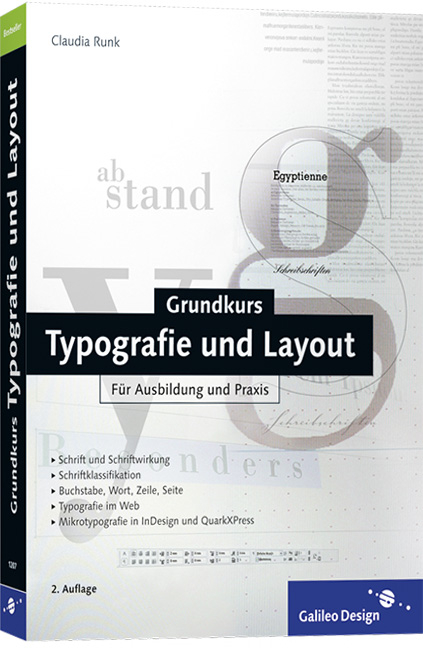
Grundkurs Typografie und Layout
Aus dem Inhalt:
- Schrift
- Schriftgeschichte, Schriftkünstler
- Schriftwahl und Schriftwirkung
- Schriftklassifikation
- Buchstabe, Zahl, Zeichen
- Abstand, Laufweite, Ausrichtung
- Serifen, Ligaturen
- Einzug und Initial
- Typo in InDesign & QuarkXPress
- Seite und Raumaufteilung
- Zeilen und Spalten
- Papierformate, Satzspiegel
- Gestaltungsraster, Bildplatzierung
- Registerhaltigkeit, Beschnitt
- Layoutfehler vermeiden
- Anforderung und Wirkung
- Typografie im Web
- Schrifttechnologie
- Schreibregeln
1 Schriftentwicklung 15
1.1 Entwicklung 16
... 3500 v. Chr. und die Sumerer 16
... 3000 v. Chr. und die Hieroglyphen 17
... 1200 v. Chr. und die Phönizier 18
... 500 v. Chr. und die Griechen 19
... 100 n. Chr. und die Römische Kapitalis 20
... 800 und die Karolingische Minuskel 22
... 1000 und die Romanik 23
... 1200 und die hochgestreckte Gotik 24
... 1400 und der Beginn der Renaissance 25
... 1450 und Gutenberg 26
... 1500, die Gebrochenen Schriften und die
... Französische Renaissance-Antiqua 27
... 500 und die Kursive 28
... 1700 und Barock und Rokoko 29
... 1800 und der Klassizismus 30
... 1880 und der Jugendstil 32
... 1900, die Times und die serifenlosen Schriften 33
... 1920 und das Bauhaus 34
... 1950 und die Schweizer Typografie 36
... 70er, 80er, 90er und die Einführung des DTP 36
... 1990 bis heute 39
... Pixel- und Screenfonts 39
1.2 Schriftschnitt und Schriftfamilien 40
... Ist Italic eine Kursive? 40
... Frutiger und seine Zahlen 41
... MultipleMaster 42
... Schrift als Gebrauchsinstrument 43
... Schriftenwelle in der Industrialisierung 43
... Experten 44
... Kapitälchen 44
... Falsche Kapitälchen – ein Kapitalverbrechen? 45
1.3 Schriftklassifikation 46
... Warum überhaupt Klassen? 46
... Schriftklassifikation nach DIN 46
... 1. Klasse: Venezianische Renaissance-Antiqua 47
... 2. Klasse: Französische Renaissance-Antiqua (Mediäval) 48
... 3. Klasse: Barock-Antiqua 49
... 4. Klasse: Klassizistische Antiqua 50
... 5. Klasse: Serifenbetonte Linear-Antiqua 51
... 6. Klasse: Serifenlose Linear-Antiqua 52
... 7. Klasse: Antiqua-Varianten 53
... 8. Klasse: Schreibschriften 54
... 9. Klasse: Handschriftliche Antiqua 54
... 10. Klasse: Gebrochene Schriften 56
... 11. Klasse: Fremdsprachliche Schriften 58
1.4 DIN 16518 von 1998 58
1.5 Beinert-Matrix 59
1.6 Schriftkünstler 60
... Otl Aicher 60
... Neville Brody 61
... Tobias Frere-Jones 62
... Adrian Frutiger 63
... Claude Garamond 64
... Luc(as) de Groot 65
... Rudolf Koch 66
... Günter Gerhard Lange 67
... Hans Eduard Meier 68
... Stanley Morison 69
... Jim Parkinson 70
... Jean-François Porchez 71
... Paul Renner 72
... Werner Schneider 73
... Erik Spiekermann 74
... Ludwig Sütterlin 75
... Jan Tschichold 76
... Kurt Weidemann 77
... Hermann Zapf 78
1.7 Typografisches Maßsystem 79
... Didot-Punkt 79
... DTP-Punkt 79
... Pica-Point 79
... Typometer 80
2 Das Zeichen 83
2.1 Der Buchstabe 84
... Form 84
... Schriftgröße 85
... Der Bleisatz in wenigen Worten 86
... Kegelgröße und Schriftgröße 86
... Bleisatz und Digitalsatz? 87
... Weitere Faktoren für die Schriftgrößenmessung 88
... Schriftgröße per Versalhöhe 88
... Versalhöhenbeispiele 88
... Versalhöhen 89
... Begriffsdefinition 90
2.2 Serifen 92
... Ursprung der Serifen 92
... Serif oder SansSerif 93
... Humanistische serifenlose Schrift 94
... Der persönliche Stil 95
2.3 Ligaturen 96
... Buchstabenform 96
... Voraussetzung 97
... OpenType 97
2.4 Zahlen 98
... Arabische Zahlen 98
... Römische Zahlen 98
... Aufbau des arabischen Zahlensystems 99
... Mediäval- und Versalziffern 99
2.5 Auszeichnungen 100
... Ästhetische und optische Auszeichnungen 100
... Sparsame Verwendung optischer Auszeichnungen 101
2.6 Lesegewohnheiten 102
... Art und Weise des Lesens: die Sakkaden 102
... Ruhe zwischen den Sakkaden 103
... Erschwerte Lesbarkeit durch breite Schrift 103
... Reihenfolge der Buchstaben 103
... Die obere Hälfte des Textes 104
... Grauwert 104
2.7 Leere Räume 106
... Geviert – die feste Größe 106
... Geviert statt flexible Räume 106
2.8 Wortabstand 107
... Die optimale Größe 107
... Große Größen bei dünnen Schriften 108
... Unfreiwillige Größenänderung 108
... Manuelle Bearbeitung 109
... Optische Löcher 109
2.9 Der Zeichenabstand 110
... Automatisch optimale Laufweiten 110
... Laufweiten und Schriftgrößen 110
... Laufweiten und Einsatzzweck 110
... Unterschneidungstabellen und AFM-Dateien 112
... Standardregeln 113
... Laufweiten bei großen und kleinen Schriften 114
... Versalsatz und Kapitälchen 114
... Negativsatz 115
... Zeichenkombinationen verändern 116
... Ausgleich in der Praxis 116
... Grundsätzlich gilt … 117
2.10 Anwendung in InDesign 118
... Kerning und Laufweite in InDesign 118
... Das Kerning prüfen 119
... Die Laufweite prüfen 119
... Das gesamte Dokument überprüfen 120
... Änderung per Tastatur 120
... Kerning auf Wortzwischenräume beschränken 121
2.11 Anwendung in QuarkXPress 122
... Laufweite ändern 122
... Eintrag vornehmen 122
... Geviertgröße 123
... Laufweitenänderung per Tastaturkürzel 124
... Laufweiten prüfen und entfernen 124
... Kerning- und Laufweitentabellen 124
... Tabellen bearbeiten 125
2.12 Schreibregeln 126
... An- und Abführungszeichen 126
... Zahlen und Formeln 127
... Preise 127
... Prozent und Grad 127
... Abkürzungen 127
... Telefon, Fax, Postfach 128
... Bankleitzahlen und Kontonummern 128
... DIN- und ISBN-Nummern 128
... Striche 128
... Divis 128
... Halbgeviertstrich 128
... Geviertstrich 129
... Auslassungspunkte 129
2.13 Kurzbefehle Adobe InDesign 130
2.14 Kurzbefehle QuarkXPress 131
3 Wort und Zeilen 134
3.1 Ausrichtung 134
... Flattersatz und Rausatz 135
... Links- und rechtsbündig 136
... Mittelachsensatz 137
... Silbentrennzone in XPress und InDesign 137
... Freier Satz und Formsatz 138
... Blocksatz 138
... Die Variablen 139
... Veränderung der Zeichenbreite 140
... Verändern der Zeichen- und Wortabstände 140
... Grenzwerte 141
... Blocksatz in QuarkXPress 142
... Blocksatz in InDesign 142
... Grenzen überschreiten 143
... Trennung oder optimaler Abstand 143
... Adobe-Absatzsetzer in InDesign 144
... Der Randausgleich: hängende Interpunktion 144
... Entscheiden Sie sich! 144
3.2 Die Zeilenlänge 146
... Zu lange Zeilen werfen aus der Reihe 146
... Zu kurze Zeilen strengen Auge und Verstand an 146
... Satzbreite 148
... Zeilenbreite und Zeilenabstand 148
3.3 Der Zeilenabstand 149
... Durchschuss 149
... Kompress und splendid 150
... Schreib- und Sprachweise 150
... Der optimale Zeilenabstand 150
... Sonderregelungen 152
... Schrift und Zeilenabstand 153
... Mittellängen und Zeilenabstand 154
... Faustregeln zum Zeilenabstand 154
3.4 Die Spalte 155
... Optimaler Spaltenabstand: die Leerzeile 156
... Spaltenabstand mit mii 156
... Ausnahmen bestätigen die Regel 157
... Spaltenlinien 157
3.5 Umbruchfehler 158
... Das Hurenkind 158
... Der Schusterjunge 158
... Geisteshaltung und Merkhilfen 159
... Abhilfe schaffen 160
... Schummeln erlaubt 160
... Gesamten Absatz verändern 161
... Software schafft Abhilfe? 162
... QuarkXPress und Adobe InDesign 162
... Falscher Ansatz 163
3.6 Der Einzug 164
... Die optimale Größe des Einzugs erste Zeile 164
... Software-Tipp 164
... Hängender Einzug 165
3.7 Initial 166
... Hängendes Initial 166
... Der Einsatz 166
... Welches Initial für welchen Zweck 167
4 Anforderung und Wirkung 169
4.1 Leseart 170
... Verschiedene Formen des Lesens 170
... 1. Typografie für lineares Lesen 171
... 2. Typografie für informierendes Lesen 171
... 3. Typografie für konsultierendes Lesen 171
... 4. Typografie für differenzierendes Lesen 172
... 5. Typografie für inszenierendes Lesen 172
4.2 Schriftwahl und Schriftwirkung 173
... Schrift transportiert eine Meinung 173
... Wirkung auf den zweiten Blick 173
... Die Faustregeln 174
... Die Faustregeln widerlegen 176
... Ein bisschen Serifen 176
... Größenabhängige Wahl 177
... Zwingende Umstände bei der Schriftwahl 178
... Ein einfacher Trick – die Gegenüberstellung 178
... Ist das Gegenteil schon Kunst? 179
4.3 Schriftkombination 180
Semantische Typografie 183
5 Typografie im Web 185
5.1 Online Lesen 186
... Typografische Beschränkungen und Möglichkeiten 186
... CSS 187
... Format und Größe 187
5.2 Kontrast und Farbe 188
... Leere Räume 189
5.3 Zeilen und Schrift 189
... Schriftgröße 190
... 72 ppi und 96 ppi 191
... Zwingende Umstände für eine Schrift 192
... Schriftwahl für Online-Medien 193
... Bildschirmschriften 195
... Empfehlungen 195
... Schriften für sehr kleine Schriftgrößen 195
... Kanten glätten 196
... Auszeichnungen im Web 197
... Textmengen begrenzen oder aufteilen 197
5.4 Das PDF-Format 197
... Einsatzgebiet des PDF 199
6 Die Seite 201
6.1 Raumaufteilung 202
... Das Vor-Layouten 202
... Eine grobe Skizze erstellen 202
... Grenzen durch Gestaltungsvorgaben 204
... Optimal verpackte Information 204
... Von groß nach klein gestalten 205
... Checkliste von groß nach klein 205
6.2 Papierformat 206
... DIN-Format 206
... DIN-Reihen 206
... Grundfläche 206
... Der goldene Schnitt 208
... Fibonacci 208
... Unbewusste harmonische Aufteilung 209
... Unübliche Formate 209
... Einfache Grundregeln 210
... Textausrichtung 210
... Optische Mitte 211
... Verschiedene Raumaufteilungen 212
... Vertikaler Text 214
... Stufen 214
... Beurteilung in QuarkXPress 215
... Beurteilung in Adobe InDesign 215
6.3 Satzspiegel 216
... Stegbreiten 216
... Berechnung des Satzspiegels 217
... Doppelseitiger Satzspiegel mit Linienkonstruktion 218
... Wer ängstlich oder unschlüssig ist 220
... Doppelseitiger Satzspiegel nach dem goldenem
... Schnitt 220
... Doppelseitiger Satzspiegel nach Neunerteilung 222
... Verschiedene Konstruktionen, ähnliche Ergebnisse 222
... Einseitiger Satzspiegel 222
... XPress und InDesign 223
... Korrekturen im Kleinen 224
... Berechnung 224
... Visuelle Kontrolle 225
6.4 Gestaltungsraster 226
... Breiten und Höhen 227
6.5 Randabfallende Elemente 228
... Beschnitt erstellen 229
... Beschnitt in QuarkXPress 230
... Beschnitt in InDesign 231
6.6 Bildplatzierung 232
... Platzierung von Bildern und anderen Objekten 232
... Platzierung im Groben 232
... Platzierung im Feinen 232
... Und wieder das Gestaltungsraster 234
... Abstand zwischen Bild und Bildunterschrift 234
... Abstand zwischen Bild und Fließtext 234
6.7 Registerhaltigkeit 235
... Qualität durch registerhaltigen Text 235
... Wer sollte registerhaltig sein? 236
... Magnetisches Raster in der Software 236
... Vorteile des magnetischen Rasters 237
... Drei Funktionen des Rasters 237
... Registerhaltigkeit in QuarkXPress 238
... Registerhaltigkeit in InDesign 239
6.8 Kolumnentitel und Pagina 240
6.9 Marginalien 241
6.10 Linien 243
... Linie und Strich 243
6.11 Regeln und Beispiele 244
... Tipps für den Seitenaufbau 244
... Beispiele 246
7 Gesamtkomposition 251
7.1 Vorbereitung 252
... Aufbau eines Layouts am Beispiel eines Magazins 252
... Dokument anlegen 252
... Gestaltungsraster 253
7.2 Bildplatzierung 253
... Bildunterschriften 254
7.3 Text 255
... Headline 255
... Vorspann 256
... Grundtext 257
... Größe der Zwischenüberschrift 257
... Ausrichtung der Zwischenüberschrift 258
... Die Platzfrage 258
... Berechnung der Abstände bei der
... Zwischenüberschrift 259
... Zweizeilige Zwischenüberschrift 260
... Stolperfallen 261
7.4 Variationen und Wiedererkennung 262
... Variationen 262
... Wiedererkennung 263
7.5 Schmückende Elemente 264
... Zitate 264
... Kontrast und Farben 265
... Sieben Prinzipien des typografischen Kontrasts 266
7.6 Kleine Änderung, große Wirkung 269
... Die Anzeige, erster Teil 269
... Die Anzeige, zweiter Teil 270
... Die Anzeige, dritter Teil 271
... Die Anzeige, vierter Teil 272
... Die Anzeige, fünfter Teil 272
... Die Visitenkarte 274
7.7 Die schwarze Liste 276
8 Schrifttechnologien 281
8.1 PostScript und TrueType 282
... PostScript 282
... EPS 282
... Die Entstehung von PostScript und TrueType 283
... Der Adobe Type Manager 283
... Probleme mit TrueType 283
... Die Basis 284
... Outline-Font 284
... Schlechter Ruf 285
... Vorteile von PostScript 285
... Hinting 286
... Unabhängige Schriftgröße 287
8.2 MultipleMaster 288
... Das Beispiel Myriad 288
8.3 OpenType 290
... Weiterentwicklung des TrueType-Formats 290
... Vorteil: problemloser Plattformwechsel 290
... Vorteil: erweiterter Zeichensatz 290
... Vorteil: erweiterte typografische Funktionalität 292
... Bedingung 1: Die Zeichenbelegung 293
... Bedingung 2: Betriebssystem und Applikation 294
... Die Software 294
8.4 Dfonts 295
8.5 Was ist 296
... Unicode 296
... ASCII 296
... 8-Bit-Zeichensatz 296
9 Glossar 299
Index 310